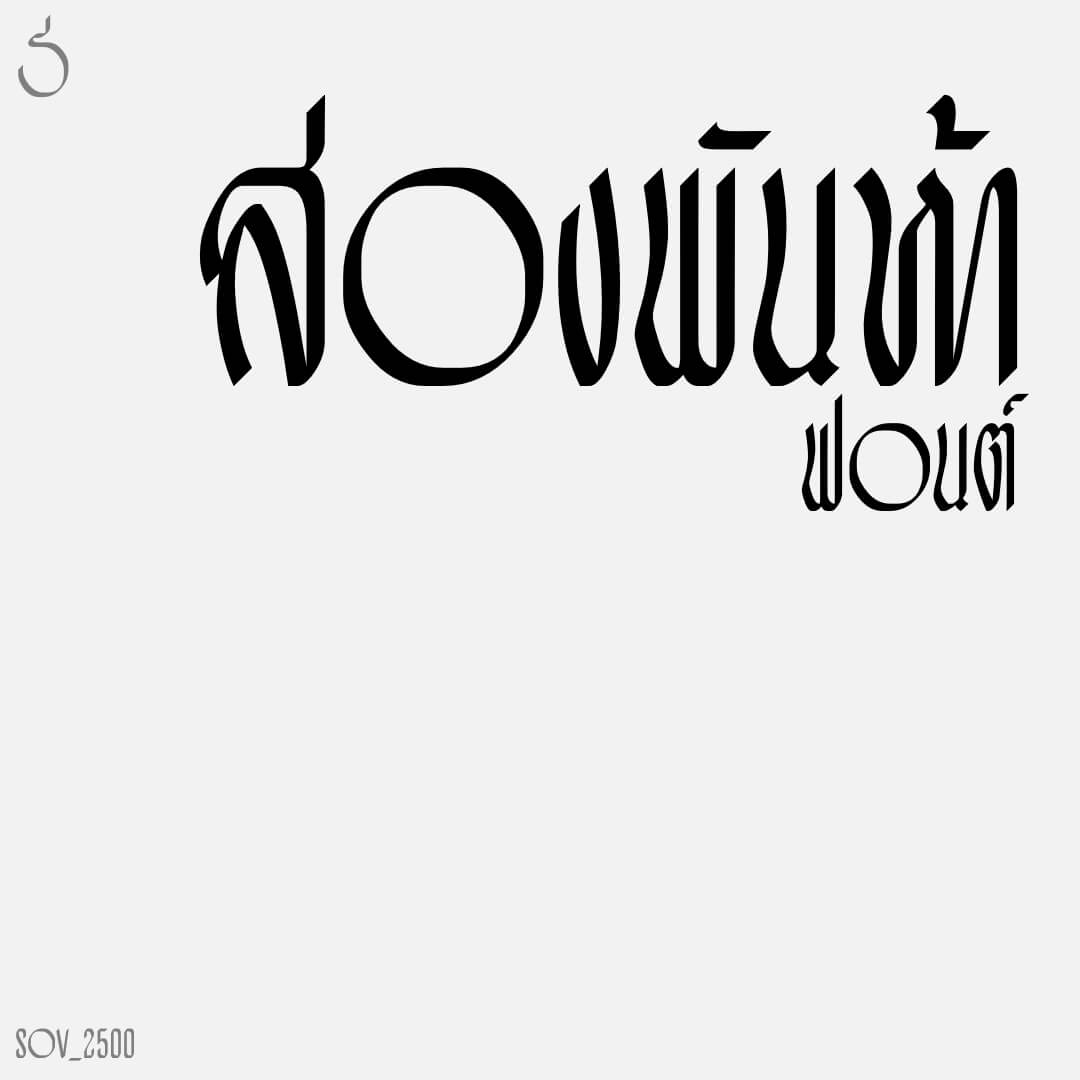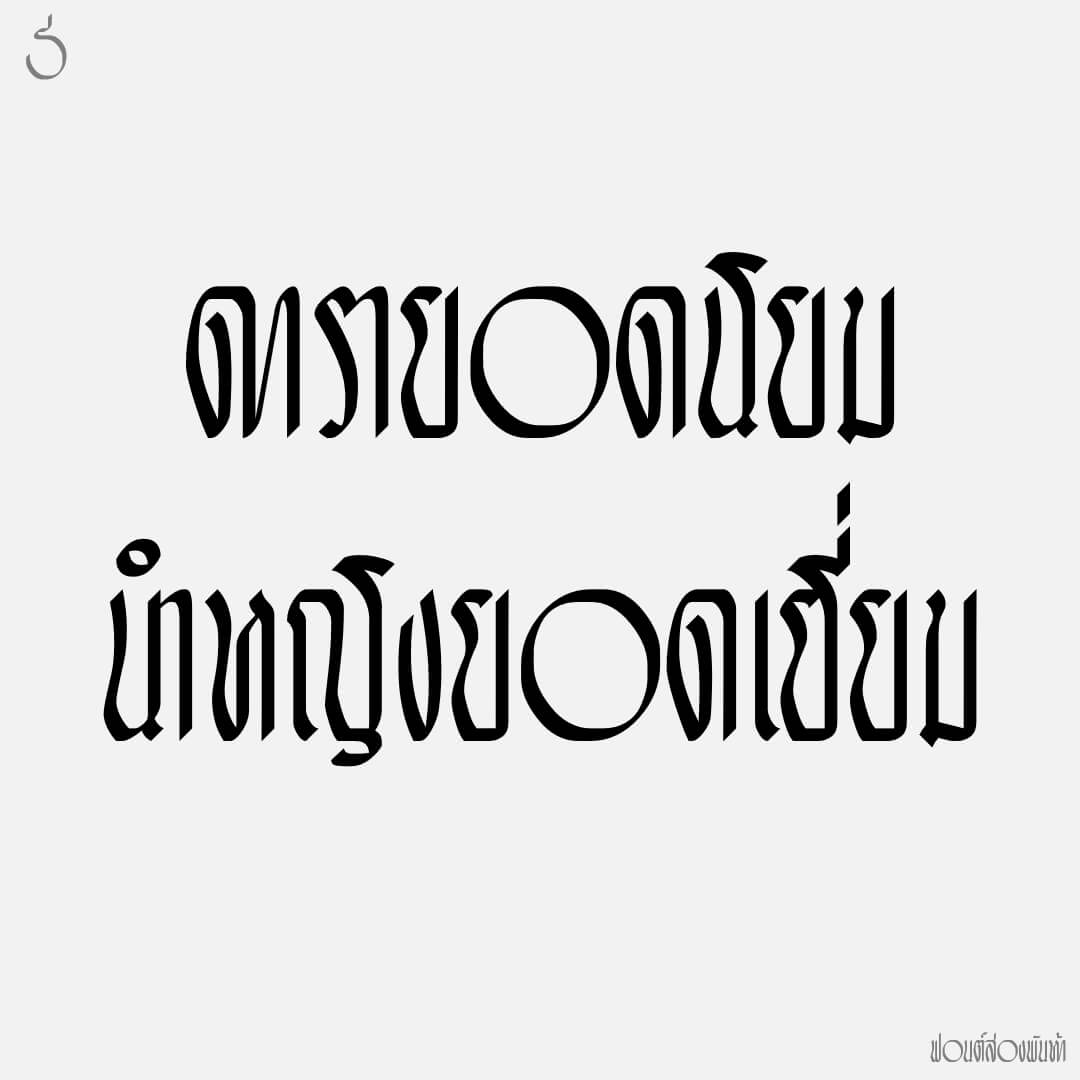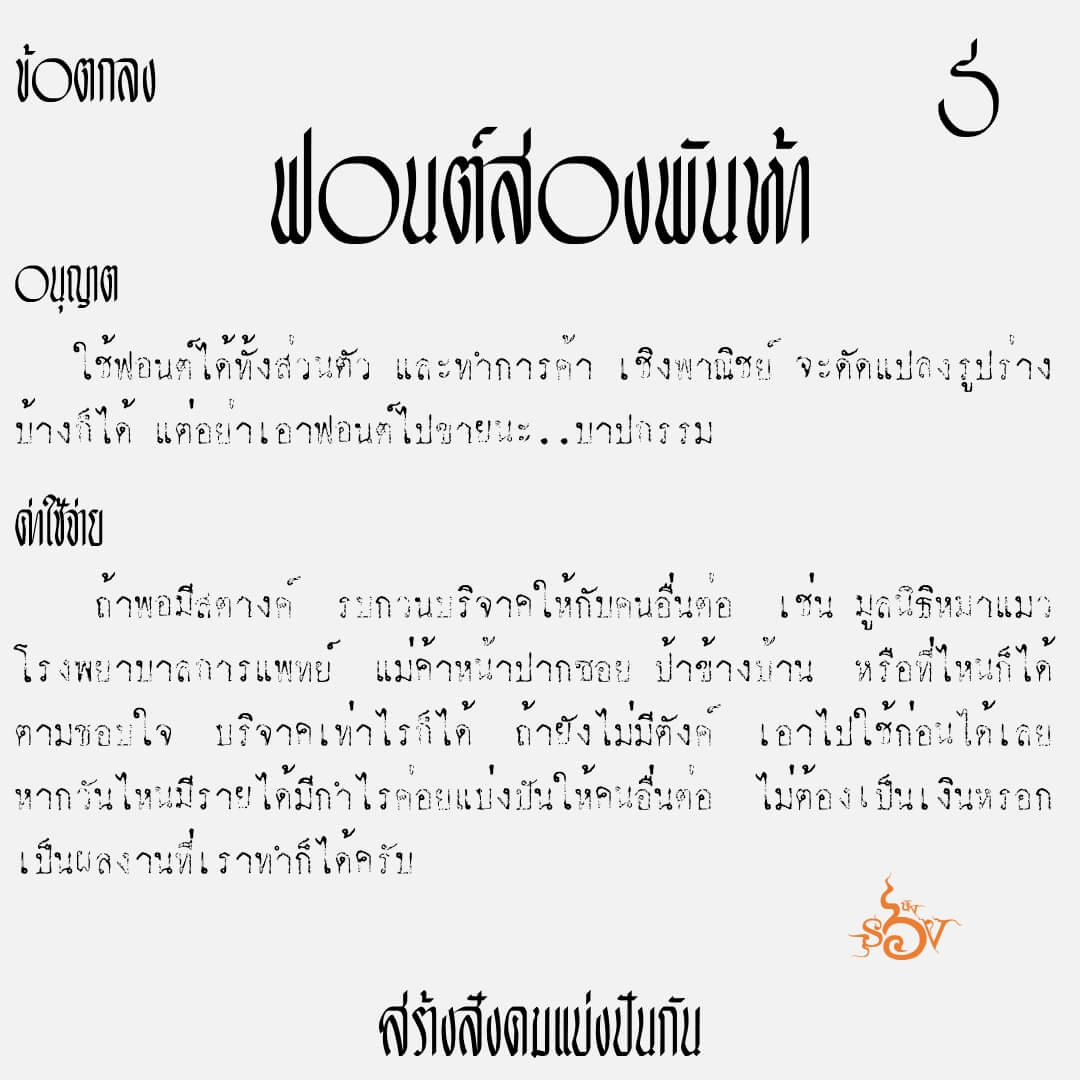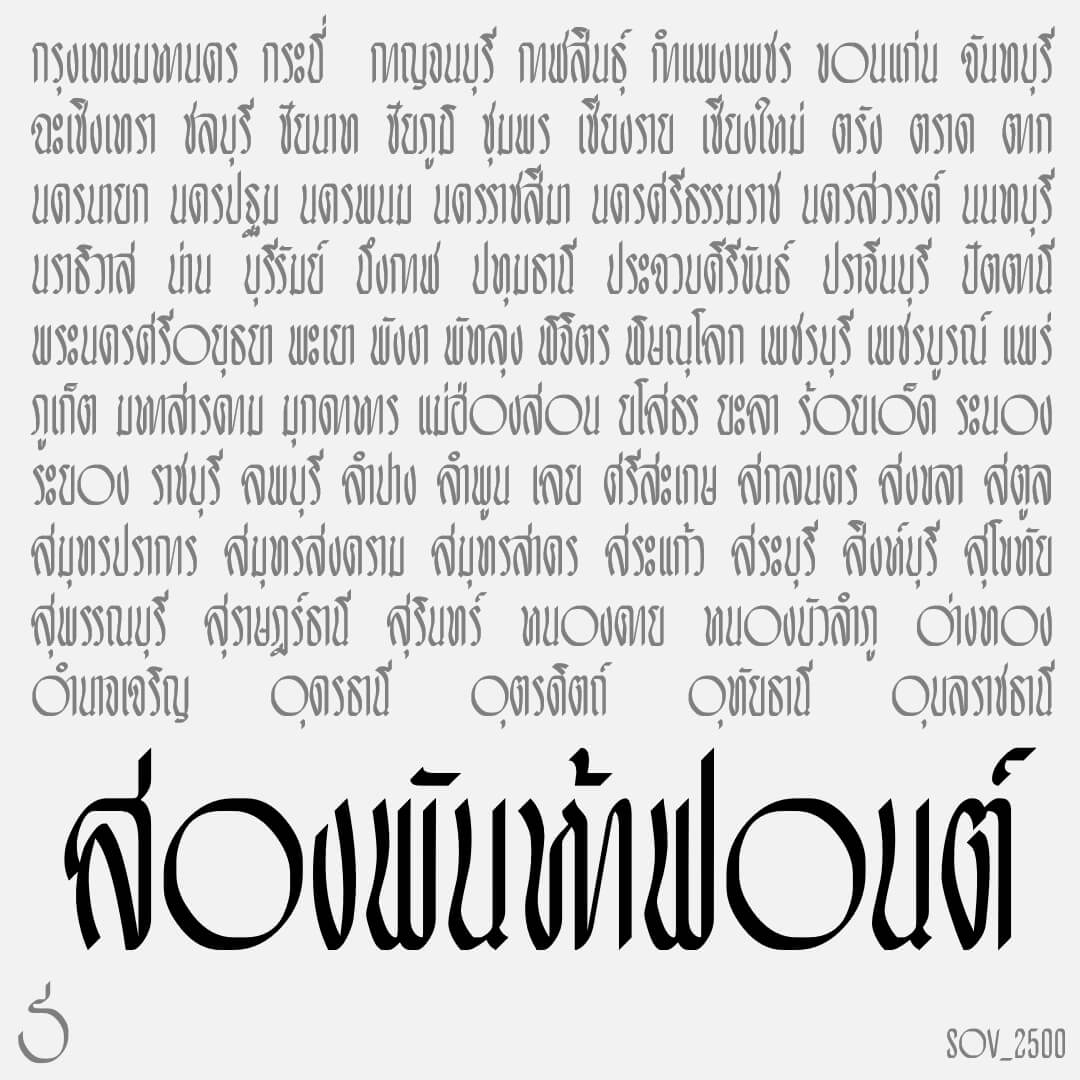
ฟอนต์สองพันห้า – แนวทางจากลายมือยอดนิยมช่วงปี ๒๕๐๐ แต่ปรับมาใช้เส้นแบบตัวนริศ ทรงผอมเพรียว แต่… มันจะมีอยู่ตัวนึง!!
เบื้องหลังการออกแบบ : ฟอนต์ สองพันห้า
สองพันห้า (SOV_2500)